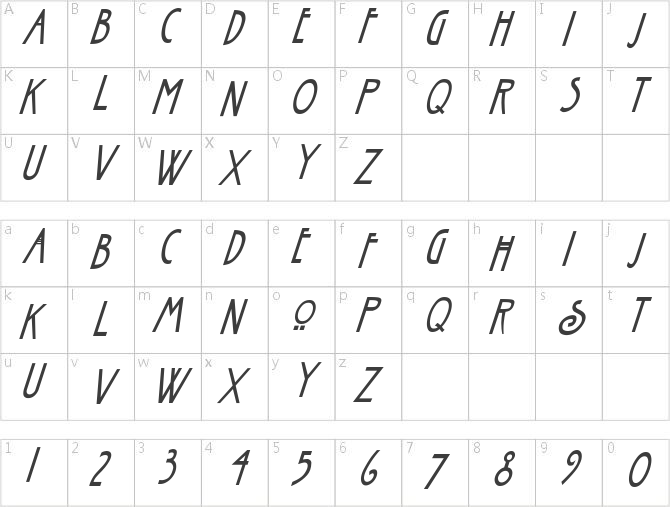
Esmount-Condens 詳情頁
字體名稱: Esmount
Esmount-Condens
Esmount-Condens字體字庫是一款讓人賞心悅目、百看不厭的英文字體,適合各類廣告和產(chǎn)品包裝設計應用,字體大小0.02MB,格式為ttf字體,上傳用戶是afig,作者/版權方為未知